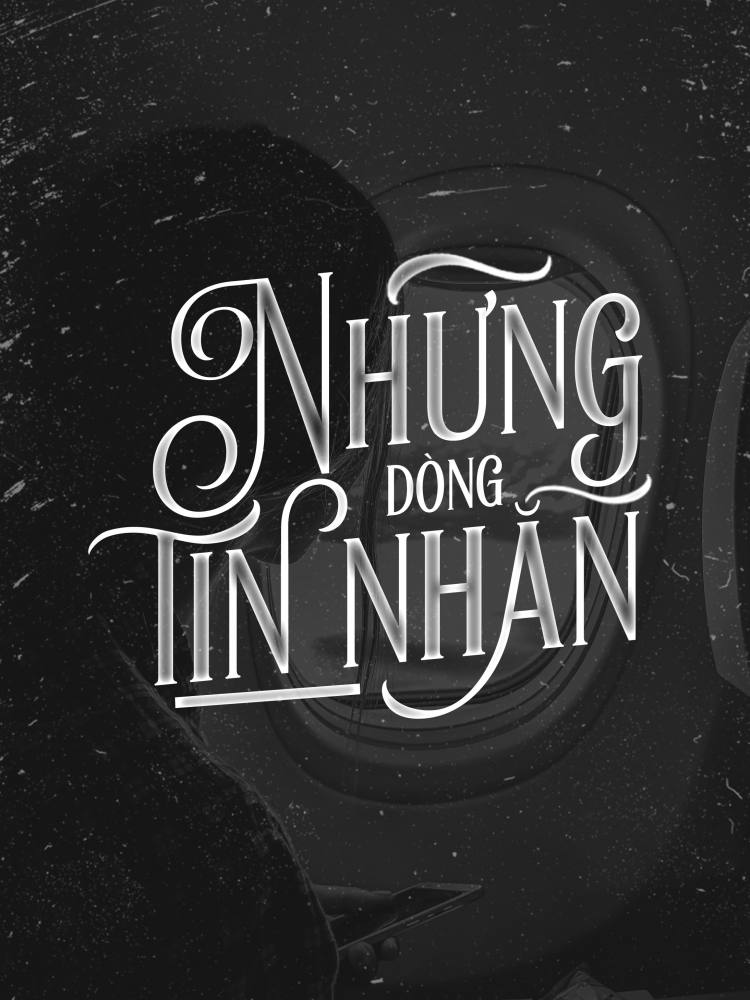
Font việt hoá MTD Artisan
Tải Font việt hoá MTD Artisan – Bộ Phông Chữ Thủ Công Độc Đáo Cho Thiết Kế
Giới thiệu về Font việt hoá MTD Artisan
Trong thế giới đồ họa hiện đại, việc tìm kiếm một mẫu Font Miễn Phí có cá tính riêng luôn là ưu tiên hàng đầu của các nhà thiết kế. Font việt hoá MTD Artisan là một tác phẩm nghệ thuật lấy cảm hứng từ nét vẽ tay thủ công, mang đến cảm giác mộc mạc và chân thực. Với sự tinh tế trong từng đường nét, bộ font này không chỉ đơn thuần là công cụ soạn thảo mà còn là linh hồn cho các sản phẩm sáng tạo. Phiên bản Việt hóa bởi MTD giúp người dùng dễ dàng sử dụng tiếng Việt có dấu một cách trơn tru, không lo lỗi font khi thiết kế.
Đặc điểm nổi bật của MTD Artisan
Bộ phông chữ này sở hữu phong cách cổ điển kết hợp hiện đại, rất phù hợp cho các dự án thiết kế logo, bao bì sản phẩm hoặc thiệp mời. Font việt hoá MTD Artisan nổi bật với các nét thanh đậm tự nhiên, tạo nên sự gần gũi và ấm áp. Đặc biệt, các ký tự được căn chỉnh tỉ mỉ, giúp văn bản duy trì được sự cân đối dù trình bày ở khổ lớn hay nhỏ. Đây là lựa chọn tuyệt vời cho những ai muốn truyền tải thông điệp mang tính cá nhân hóa cao.
Ứng dụng thực tế của Font việt hoá MTD Artisan
Nhờ tính linh hoạt, Font việt hoá MTD Artisan được ứng dụng rộng rãi trong nhiều lĩnh vực khác nhau. Trong giáo dục, thầy cô và học sinh có thể dùng font này để trang trí slide bài giảng hoặc làm báo tường sinh động. Trong kinh doanh, các quán cà phê hay tiệm bánh thường sử dụng Artisan để thiết kế menu và nhãn dán, tạo ấn tượng về sự thủ công, tỉ mỉ. Khả năng tương thích tốt trên các phần mềm như Photoshop hay Illustrator giúp quá trình sáng tạo trở nên chuyên nghiệp hơn bao giờ hết.